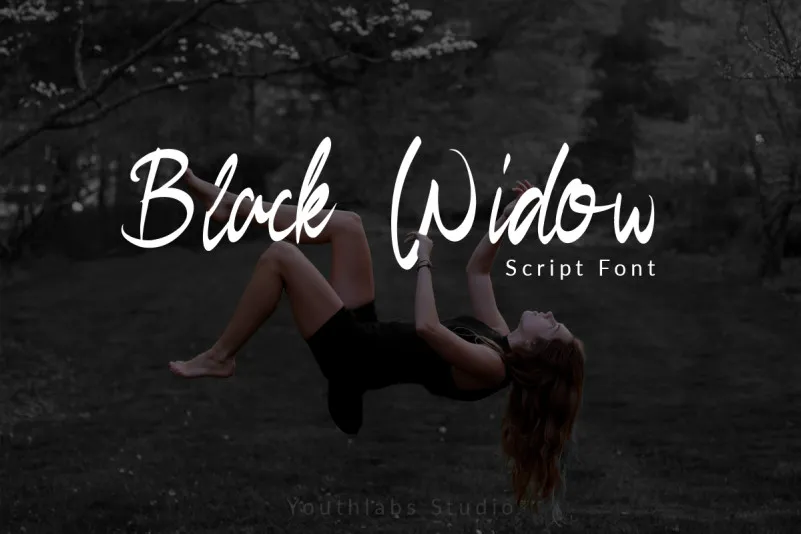
Free Black Widow Script Font – Download Grátis
A Free Black Widow Script Font é uma fonte tipográfica que inspira-se no famoso herói feminino do Universo Marvel – a Namorata Esqueleto. Inspirada no estilo elegante e poderoso dos personagens do Marvel, esta fonte foi criada para encantar os olhos em cada caractere. Baseada na técnica da calligrafia com um toque digital, ela captura a beleza da calligrafia artesanal e oferece alternâncias de caracteres que permitem uma ampla gama de possibilidades designísticas. Este é um recurso indispensável para os designers que buscam adicionar elegância e força visual aos seus trabalhos. Desenvolvida pela YouthLabs, a Free Black Widow Script Font se destaca como uma opção original e encantadora para qualquer projeto de design.